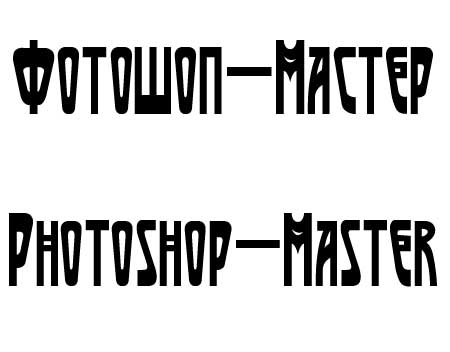
Дополнения Шрифты Татьяна Гапонова 31 марта 2009 Шрифт - Afisha Красивый шрифт в стиле старых Афиш. С поддержкой русского языка. Скачать Шрифт - Afisha